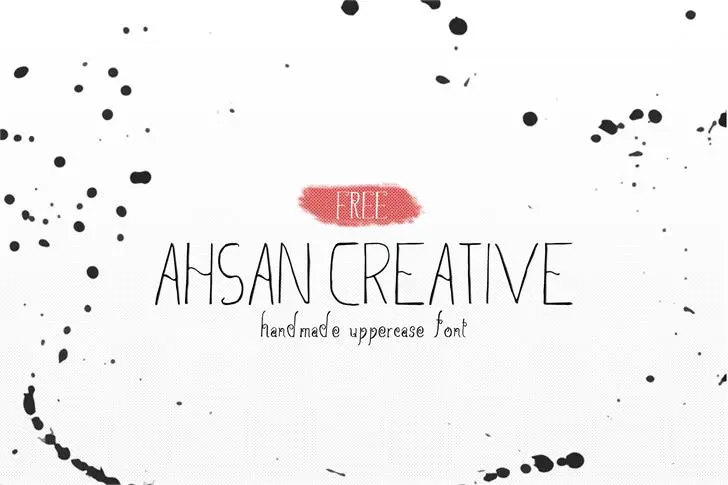
Ahsan Creative Font – Download Grátis
Bem-vindo ao mundo deliciosamente elegante da Ahsan Creative Font! Este é um tipo de display com muita energia e estilo que permite criar tipografia artesanal instantaneamente, tornando a criação de designs únicos muito mais divertida e fácil. Ahsan Creative é uma fonte criada para quem deseja trazer vida à sua designação. Seu charme elegante contrasta perfeitamente com seu caráter vibrante, permitindo que você crie texturas e logotipos impecáveis. Este tipo de escrita não apenas adicionará um toque único a seus projetos digitais, mas também dará uma sensação aconchegante e profissional aos mesmos. Com o design da fonte criado por Creativetacos, Ahsan Creative é perfeito para quem deseja expressar sua personalidade no design. Se você está procurando por um tipo de letra única que pode se adaptar a qualquer projeto – seja ele impresso ou digital, online ou offline – então Ahsan Creative está aqui para atendê-lo. Se você já conhece e adora essa fonte, certamente já passou pela página da nossa CreativeWhoa e criaramarket onde encontrará mais informações. Se ainda não conhece, é hora de descobrir a incrível magia que uma boa font pode trazer à sua criação gráfica. Seja para design de site, logotipos ou qualquer outro projeto, o Ahsan Creative Font está pronto para entregar seu trabalho de primeira linha.